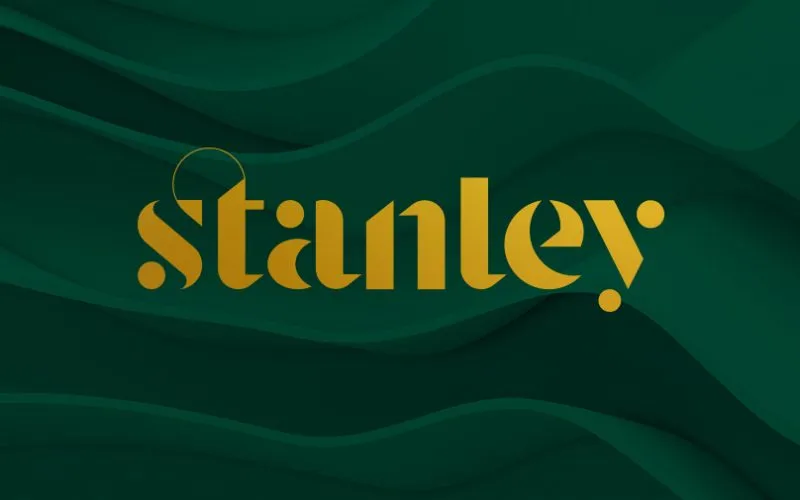
Através do designer Jérémie Gauthier, apresentamos a Stanley Font, uma tipografia para exibição deslumbrante que combina formas arredondadas e retangulares de um modo elegante. A Stanley Display Typeface é perfeitamente adequada para criações de marca, folheto, embalagens e até mesmo cartazes modernos, oferecendo beleza em cada letra do alfabeto. Uma fonte incrível para qualquer aplicação gráfica, especialmente ideal para ambientes que valorizam uma aparência sofisticada e contemporânea. Esta tipografia está disponível tanto na versão maiúscula quanto minúscula, tornando-a perfeita para uso em diversos projetos. Não hesite em experimentar Stanley Display Typeface nas próximas criações gráficas que você realizar. É uma opção que certamente deixará sua marca mais inovadora e atraente.